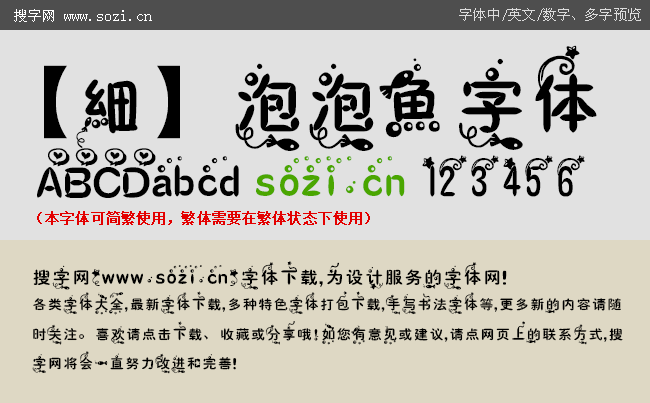
細(xì)泡泡魚字體
搜字網(wǎng)給大家提供一款細(xì)泡泡魚字體手機(jī)中文字體下載。這款手機(jī)中文字體以漢儀橄欖體為原形,在筆畫間嵌入有趣的卡通泡泡和小魚的圖形,漢儀橄欖體兩頭尖,中間呈凸圓弧形。筆畫簡(jiǎn)潔新穎,柔軟流暢,風(fēng)格稚氣質(zhì)樸,明快清純,藝術(shù)性較強(qiáng)。加入卡通圖案后更加有趣,非常適合喜歡卡通的朋友在手機(jī)上安裝使用。